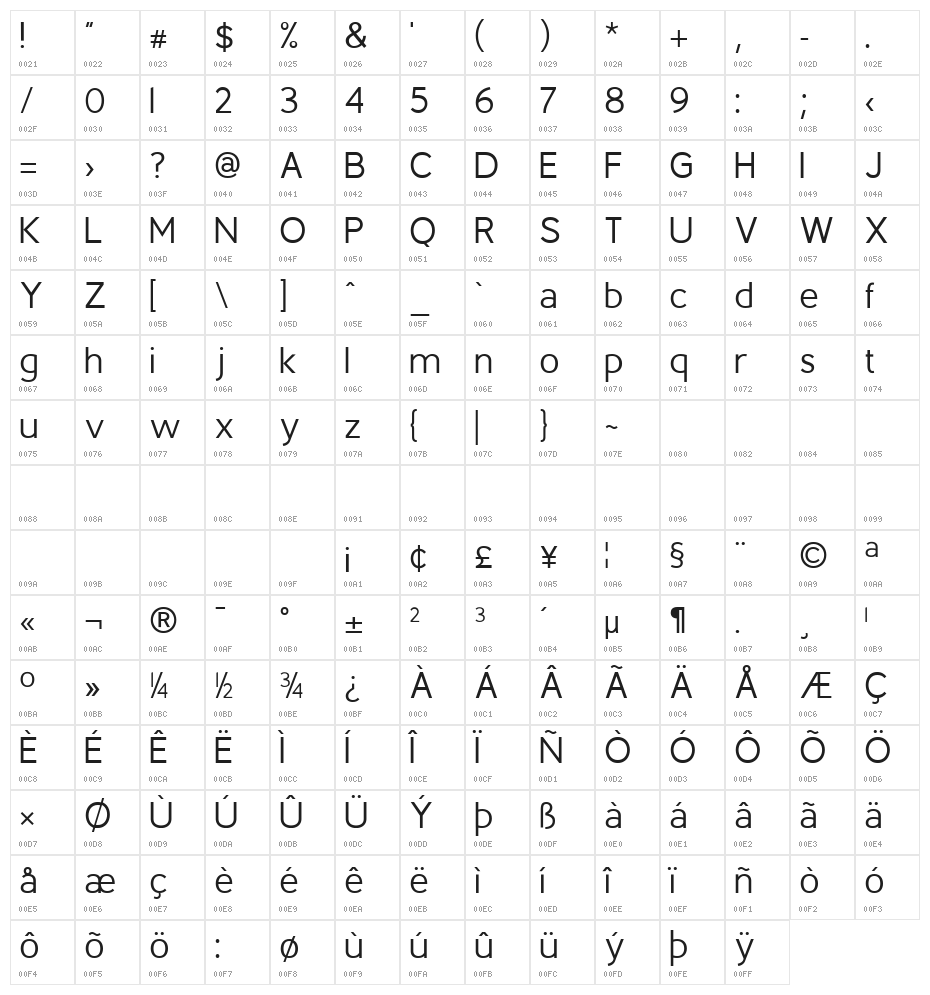
Berlin Font
✎ Sans Serif
| 使用场景 | Headlines, Logos, Branding |
| 推荐项目 | Ideal for branding, advertising, web design, and editorial layouts where a modern and clean aesthetic is desired. |